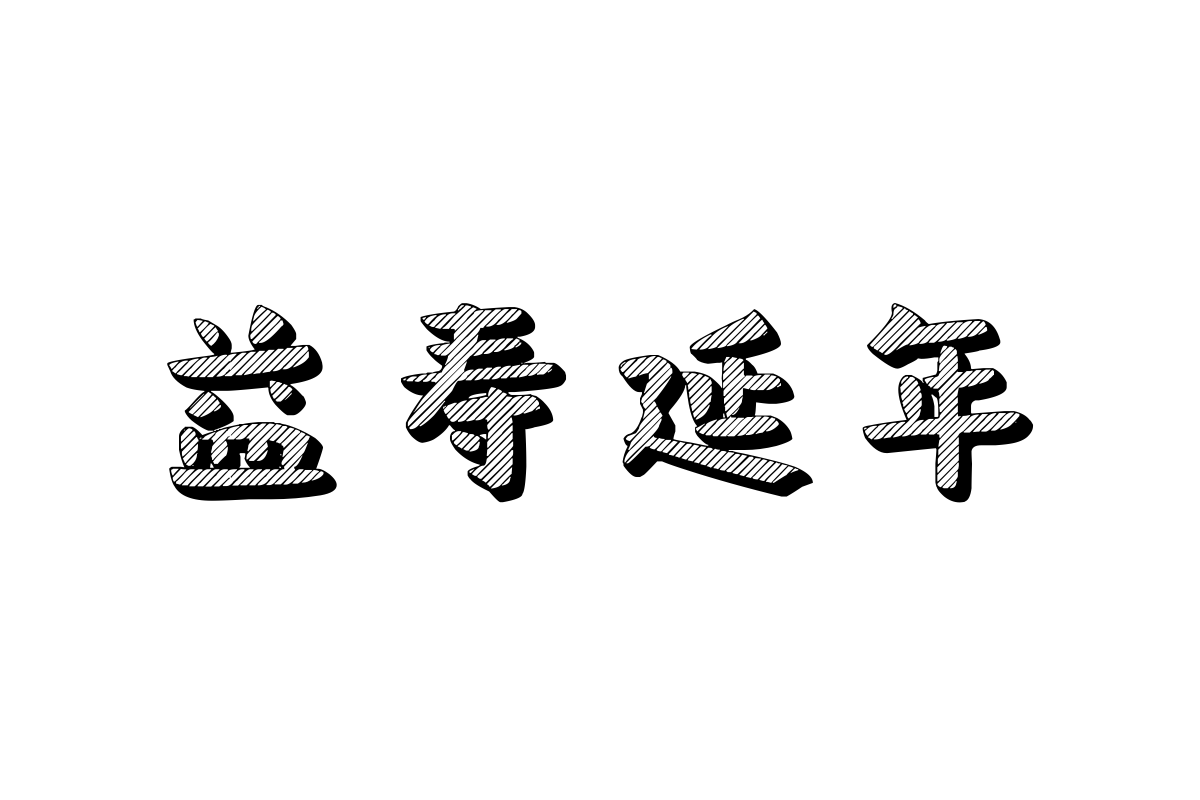
汉仪新蒂棉花糖黑板报B是一款适用于中文书写的字体,具有独特的设计风格和特点。这款字体采用了圆润、饱满的字形结构,给人一种温馨可爱的感觉。它的笔画流畅自然,易于书写,适合用于各种书写场景。同时,这款字体也具有较高的辨识度,能够吸引读者的注意力。总的来说,汉仪新蒂棉花糖黑板报B是一款非常适合用于书写黑板报的字体,无论是在教学还是其他场合,都能够展现出其独特的魅力。